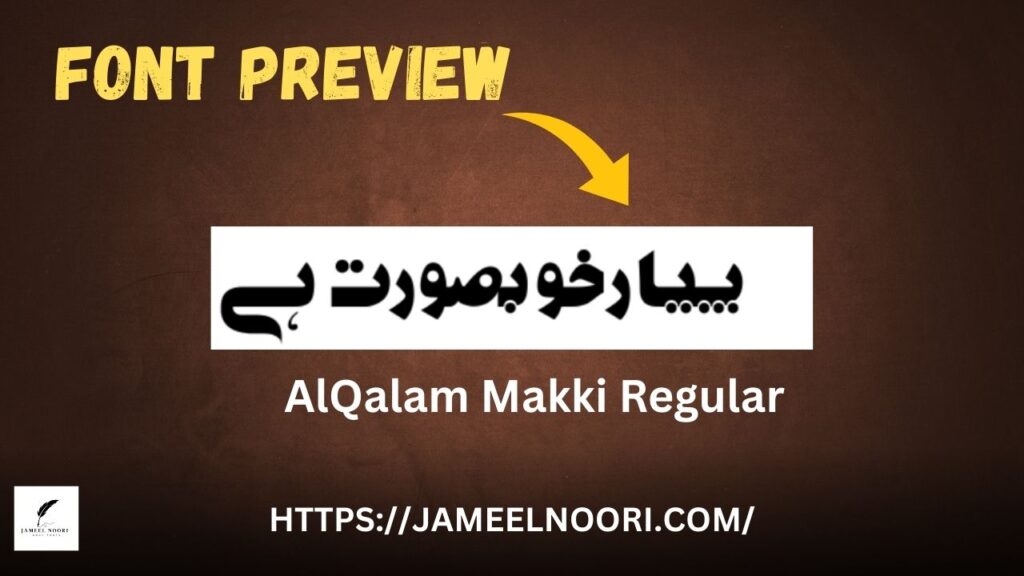
Introduction to Urdu Font AlQalam Makki
Urdu Font AlQalam Makki aik bohat hi mashhoor aur stylish Urdu font hai jo specially un logon ke liye design kiya gaya hai jo apni Urdu writing ko elegant aur readable banana chahte hain. Ye font AlQalam Makki Regular ke naam se bhi jana jata hai aur isay TrueType Font (TTF) format me download kiya ja sakta hai.
Features of Urdu Font AlQalam Makki
- Perfect readability ke saath Qurani Scripts, Books, aur Design Projects ke liye ideal hai.
| Designer | AlQalam Studio |
Uses of Urdu Font AlQalam Makki
Urdu Font AlQalam Makki ko aap following purposes ke liye use kar sakte hain:
- Urdu books aur Islamic materials likhne ke liye
- YouTube thumbnails aur posters design karne ke liye
- School aur Madrasa notes banane ke liye
- Official Urdu documents ke layout ke liye
Benefits of Using Urdu Font AlQalam Makki
- Readable aur elegant look deta hai.
Why Choose Urdu Font AlQalam Makki in Pakistan
Pakistan me Urdu likhne aur publish karne ke liye readable aur attractive font choose karna zaroori hota hai. Urdu Font AlQalam Makki aapko wo premium look deta hai jo aapki content presentation ko unique banata hai. Ye font especially Karachi, Lahore, aur Islamabad ke designers aur publishers ke darmiyan popular hai.
Conclusion – Why Urdu Font AlQalam Makki is the Expert’s Choice
Agar aap ek Urdu content creator, designer, ya student hain, to Urdu Font AlQalam Makki aapke liye perfect choice hai. Ye font simple, smooth aur highly readable hai jo aapki Urdu typography ko professional touch deta hai.
What is Urdu Font AlQalam Makki?
It is a stylish Urdu TrueType font (TTF) designed for readability and elegance.
Who created AlQalam Makki Regular font?
It was developed by AlQalam Studio.